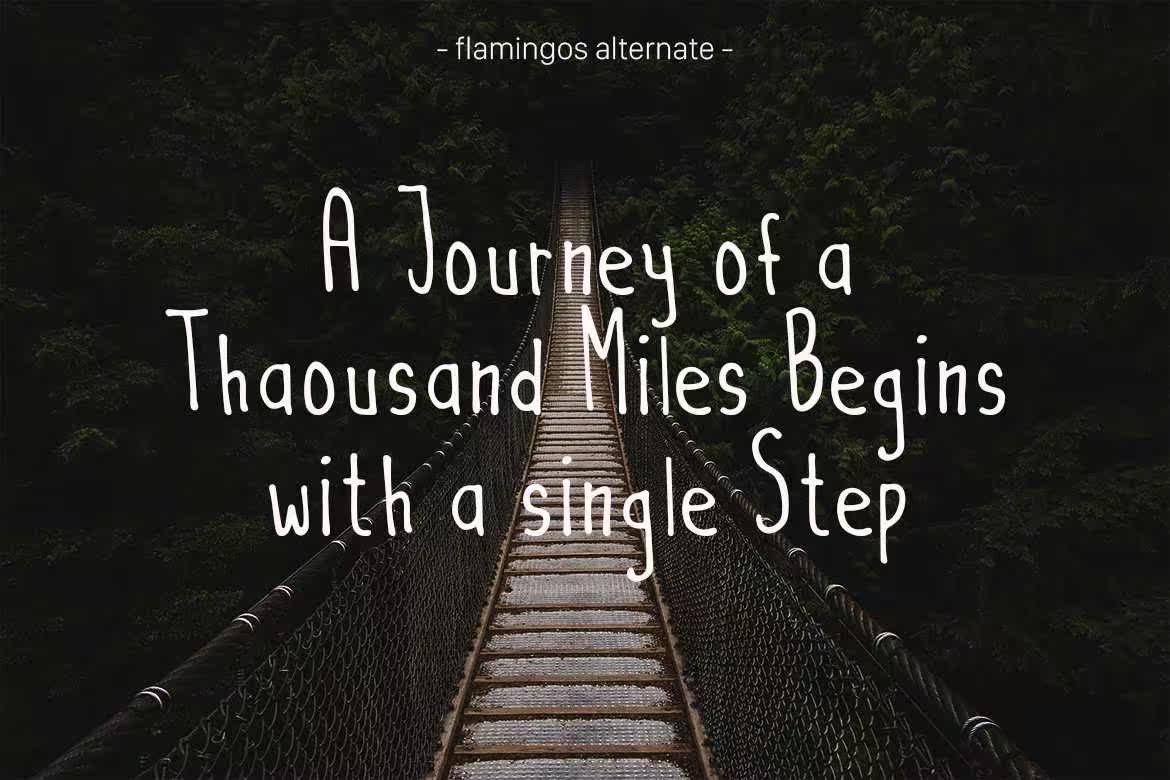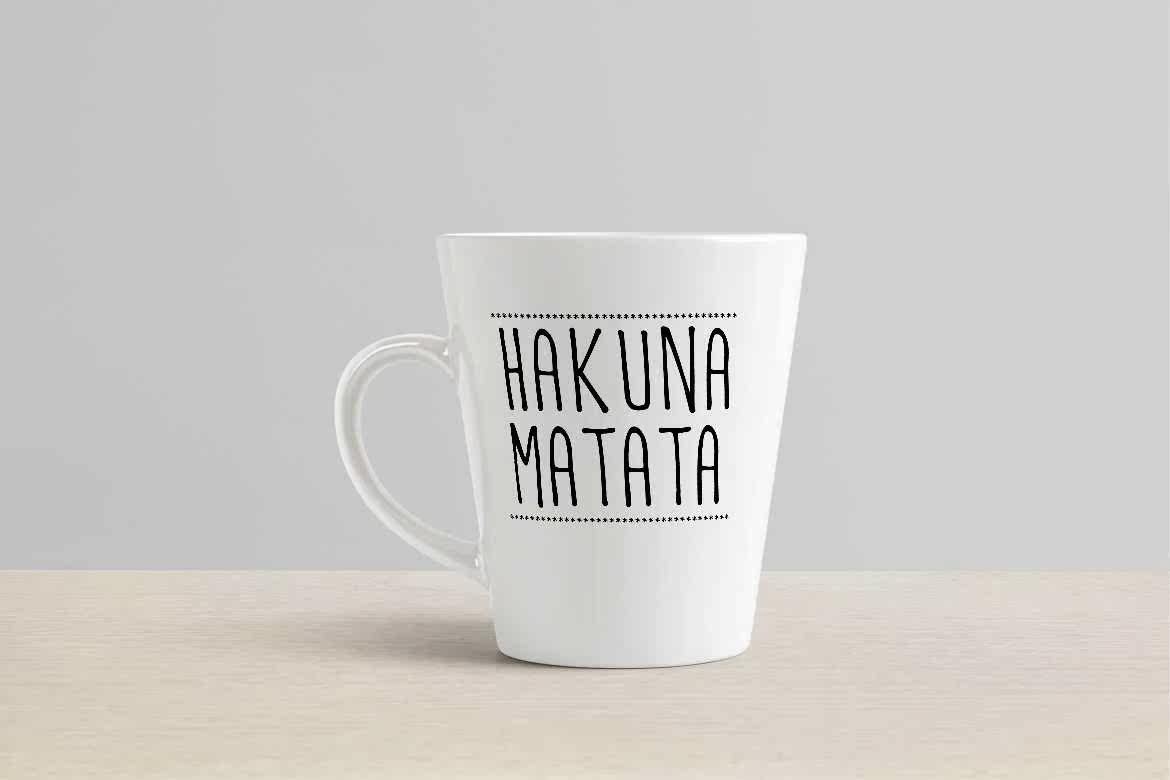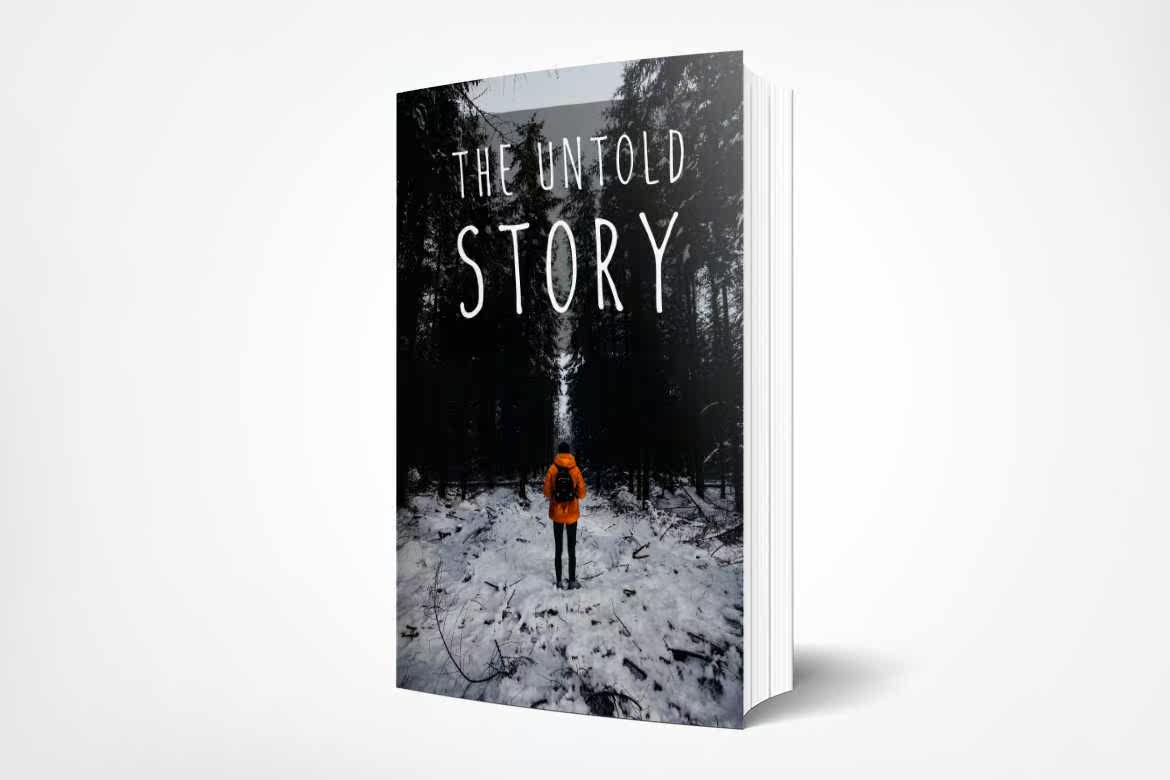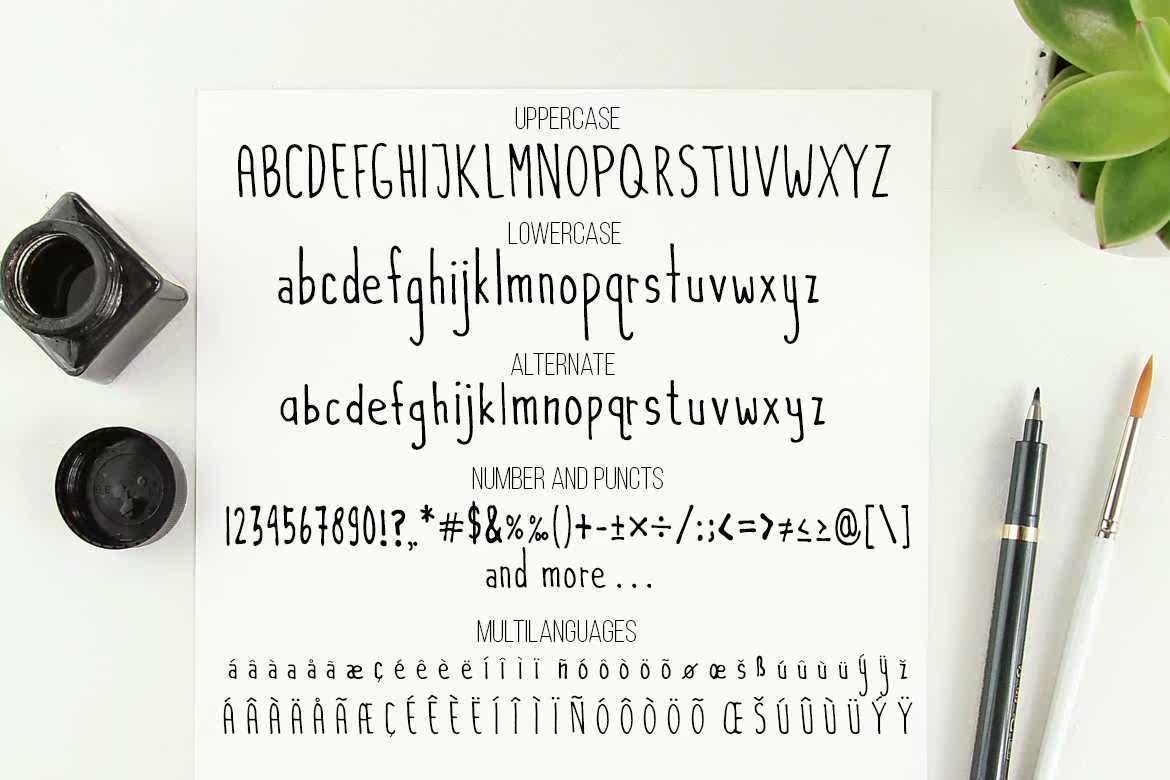
Flamingos是Kinnyan和Clean Handwriten CondensedSans serif。当使用其他字体打印时,此CondensedSans serif将完美地显示所有卡片和邀请函、封面和网络。Flamingos是品牌项目、徽标、婚礼设计、社交媒体、广告、产品包装、产品设计、标签、照片、水印、,书籍封面和需要手写品味的项目。Flamingos Kinnyan和Clean Handwriten Congregated Sans serif。当使用其他字体打印时,此Congregated Sans serif将使您的卡片和邀请函、封面书和网页看起来完美无瑕。Flamingos是品牌项目、徽标、婚礼设计、社交媒体、广告、产品包装、产品设计、标签、,需要手写的照片、水印、书籍封面和项目。